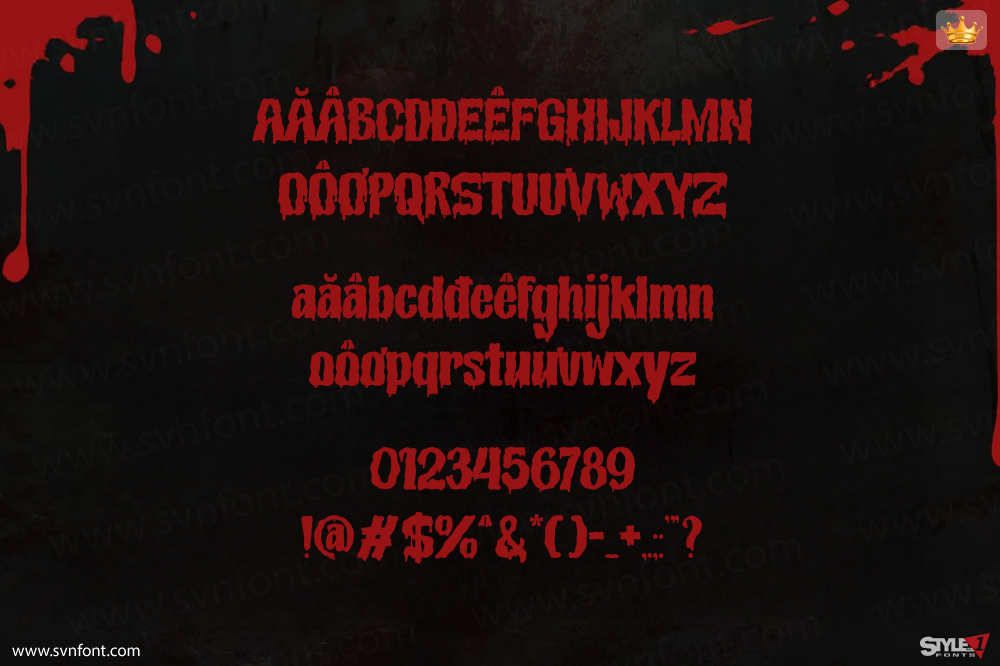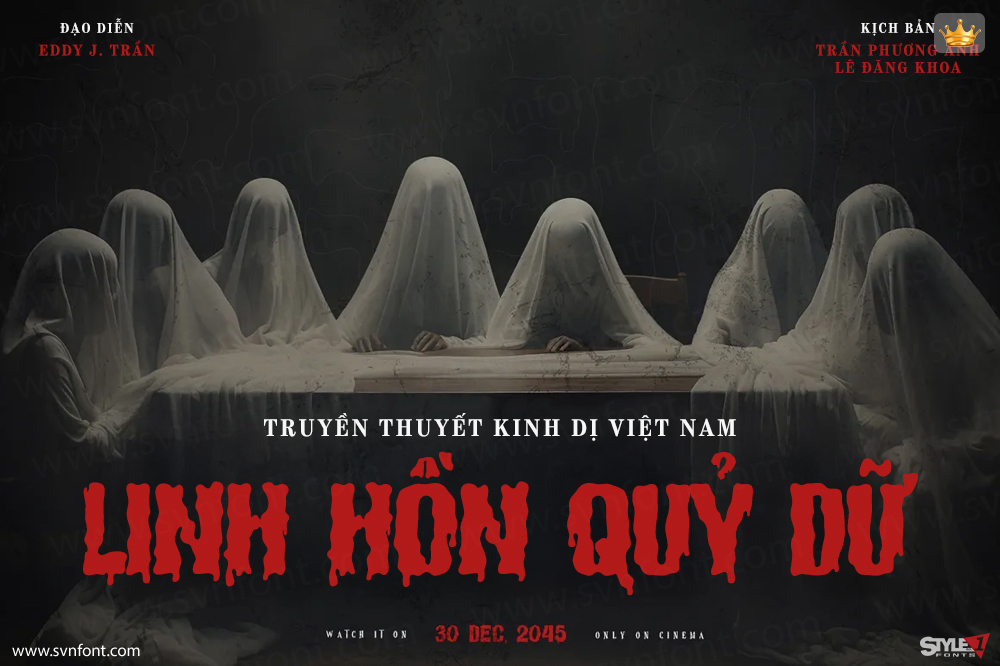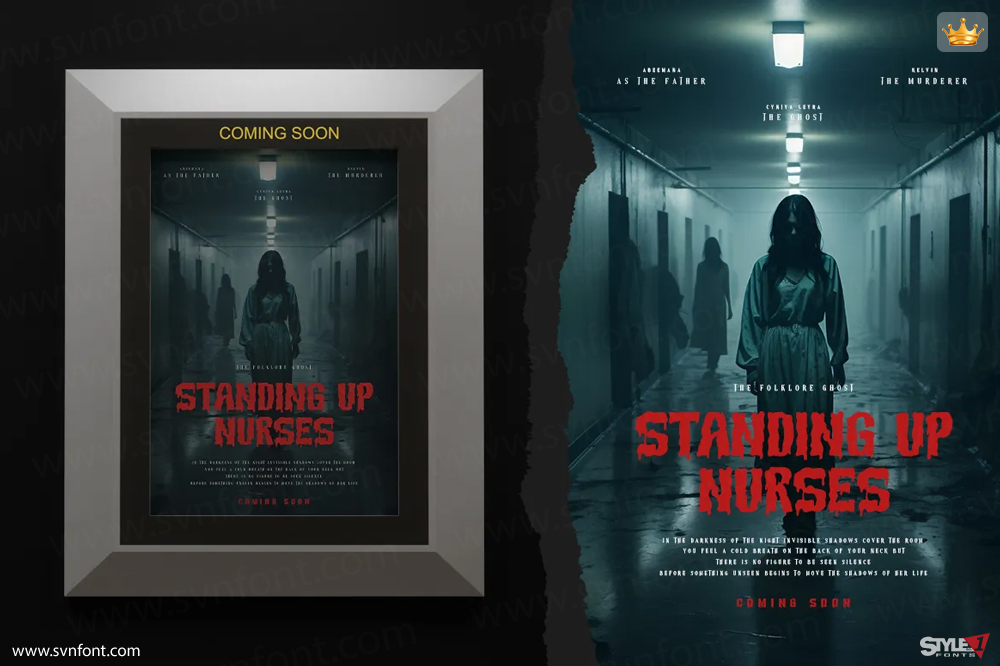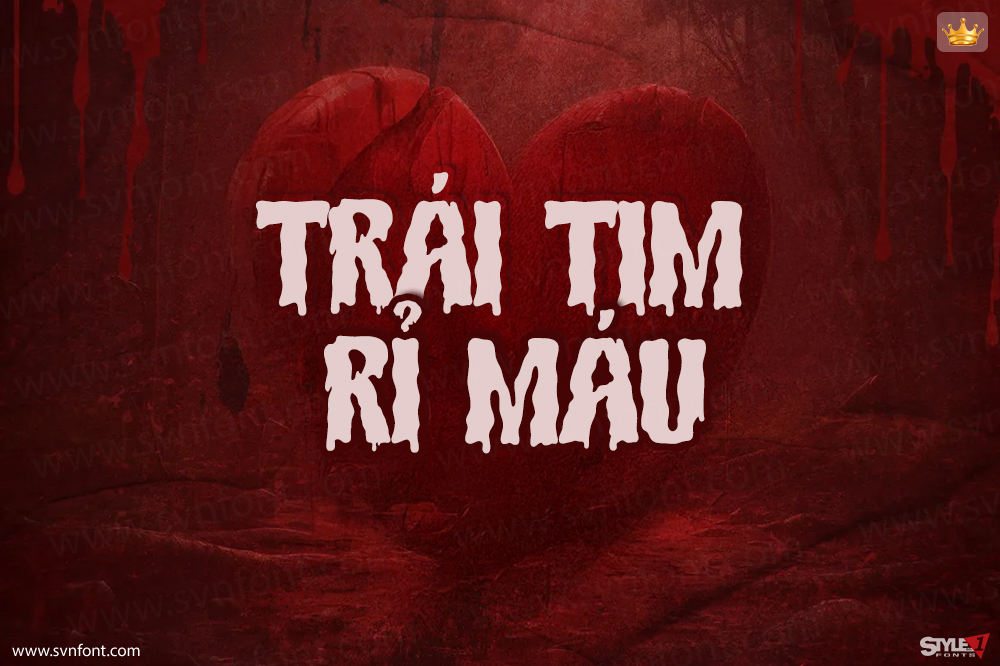
Heartbleed là một kiểu chữ kinh dị rùng rợn, được thiết kế để khơi gợi cảm giác sợ hãi và bất an. Với các ký tự sắc nét, nhỏ giọt mô phỏng máu cùng phong cách tối tăm, u ám, Heartbleed hoàn hảo cho áp phích phim kinh dị, quảng bá nhà ma, thiết kế Halloween và bìa sách ghê rợn. Kiểu chữ này nắm bắt được bản chất của sự kinh hoàng, lý tưởng cho các dự án cần tạo ra hiệu ứng hình ảnh táo bạo, lạnh sống lưng. Phong cách ma mị của Heartbleed chắc chắn sẽ để lại ấn tượng sâu sắc, tạo nên bầu không khí hồi hộp và đáng sợ.
Nhà thiết kế: typefactory
Nhà phát hành: typefactoryco